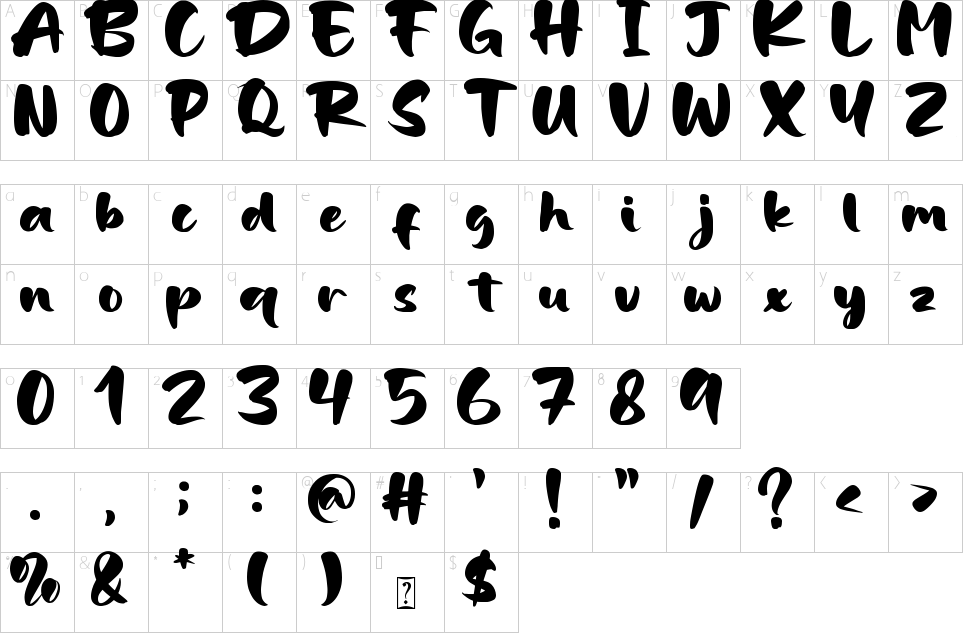
A fonte ‘Jolly Jingle Font’ é uma opção de fonte lúdica e animada, perfeita para aqueles que buscam uma aparência descontraída em suas criações digitais. Desenvolvida pelo estúdio Letterara Studio, esta fonte apresenta um tom desconcertantemente alegre, ideal para gráficos, layouts e designs de mídia social. Suas linhas curvas e texturas desenhadas cuidadosamente criam um efeito brilhante e jovial, que promete trazer vida e diversão aos seus projetos. Com sua facilidade de uso e grande variedade de opções, ‘Jolly Jingle Font’ é uma escolha ideal para projetos que precisam de um toque alegre e fresco, seja em seu formato Windows ou Mac. Com 233 downloads já registrados, a sua estabilidade e qualidade já foram testadas e aprovadas por outros designers, fazendo dela uma escolha confiável para quem busca uma fonte vibrante e de boa qualidade.